หลังจากที่กระแส Y2K ในปี 2000 กลับมาพูดถึงและแฟชั่นก็เป็นที่นิยมอีกครั้งในปัจจุบัน ทีมงานจึงมีฟอนต์ภาษาอังกฤษแนว Y2K มาแนะนำ เผื่อว่าจะนำไปตกแต่งงานกราฟิกต่าง ๆ
แนะนำ 10 ฟอนต์ แนว Y2K สำหรับตกแต่งงานดีไซน์ย้อนกลับไปปี 2000
ฟอนต์ที่นำมาแนะนำนี้ เป็นฟอนต์ที่มีกลิ่นอายของยุค Y2K สามารถนำไปใช้ตกแต่งงานกราฟิก งานโฆษณาต่าง ๆ หากสนใจนำไปใช้ด้านการศึกษา การทำงานส่วนตัวที่ไม่เกี่ยวข้องกับเชิงพาณิชย์ก็สามารถดาวน์โหลดฟรีกันได้เลย
1. Popboy Font
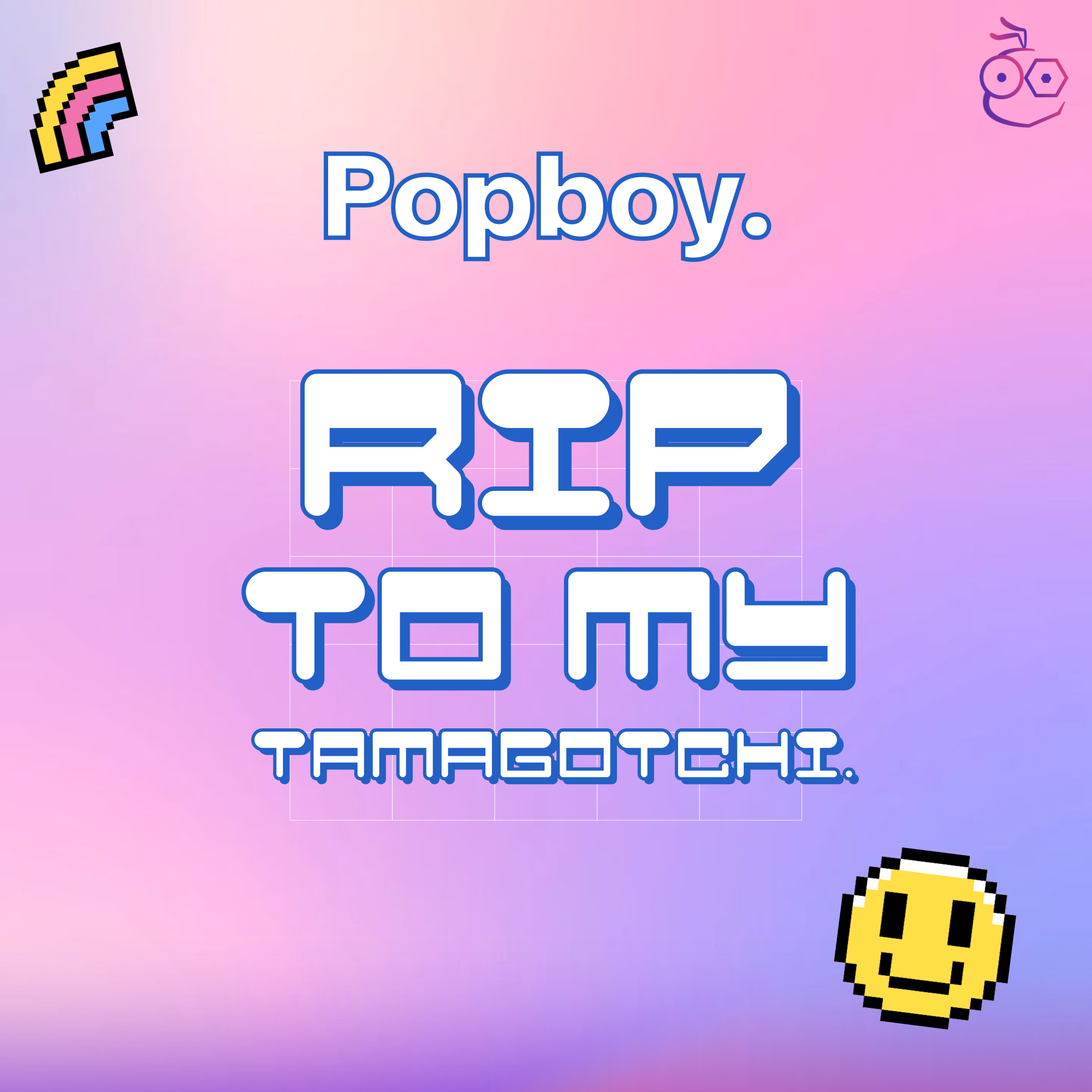
2. Planet Kosmos
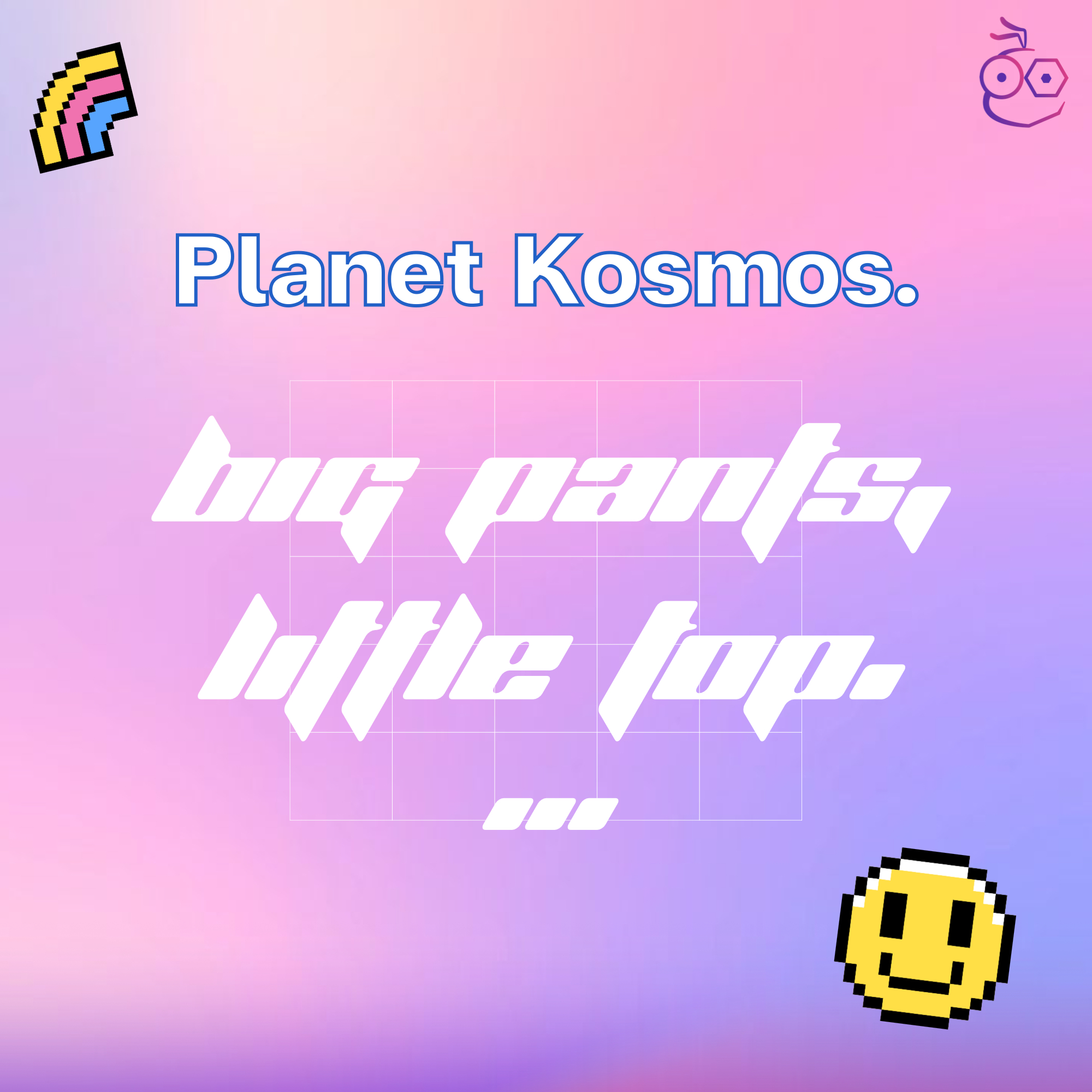
3. Troglodyte Pop
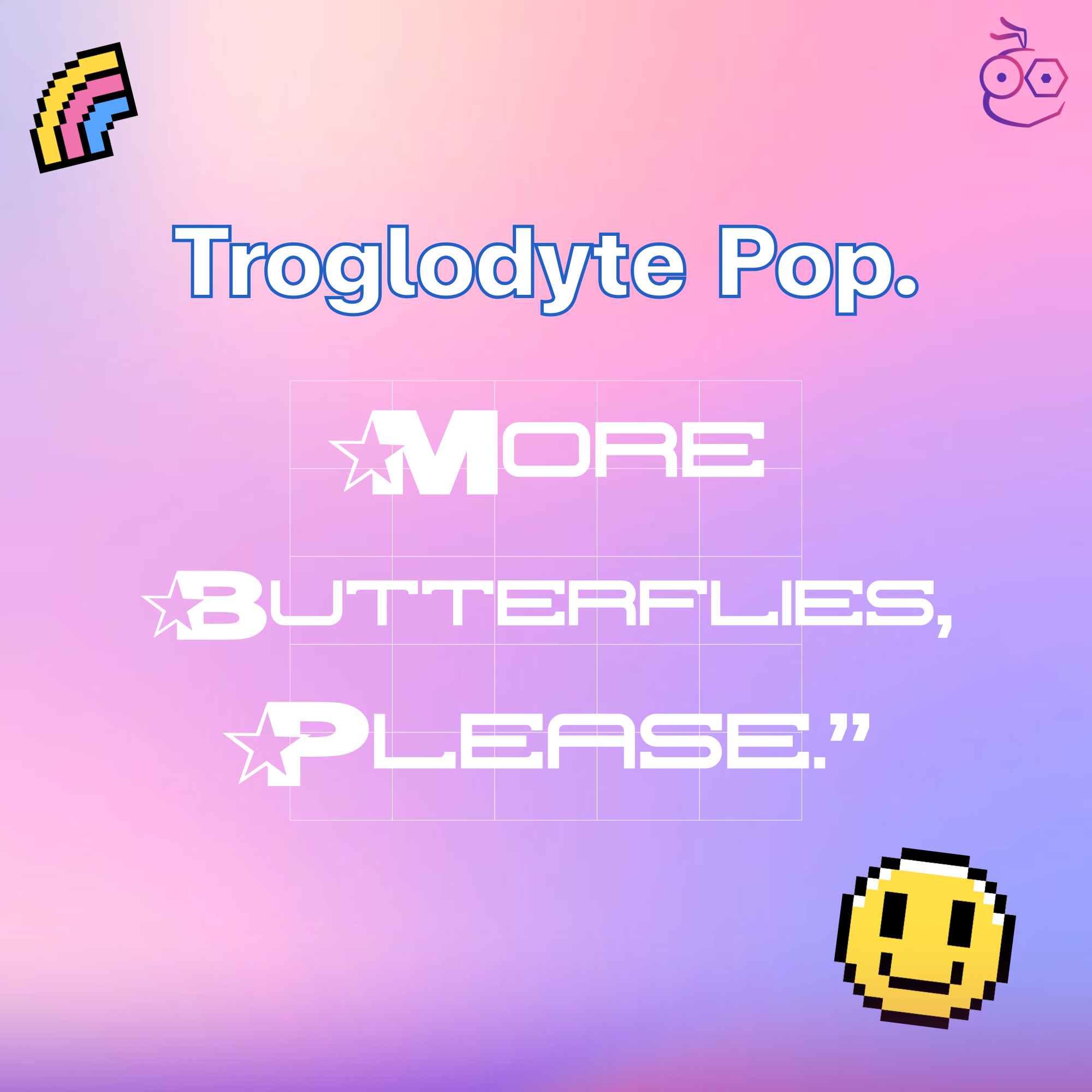
4. Bubblicious
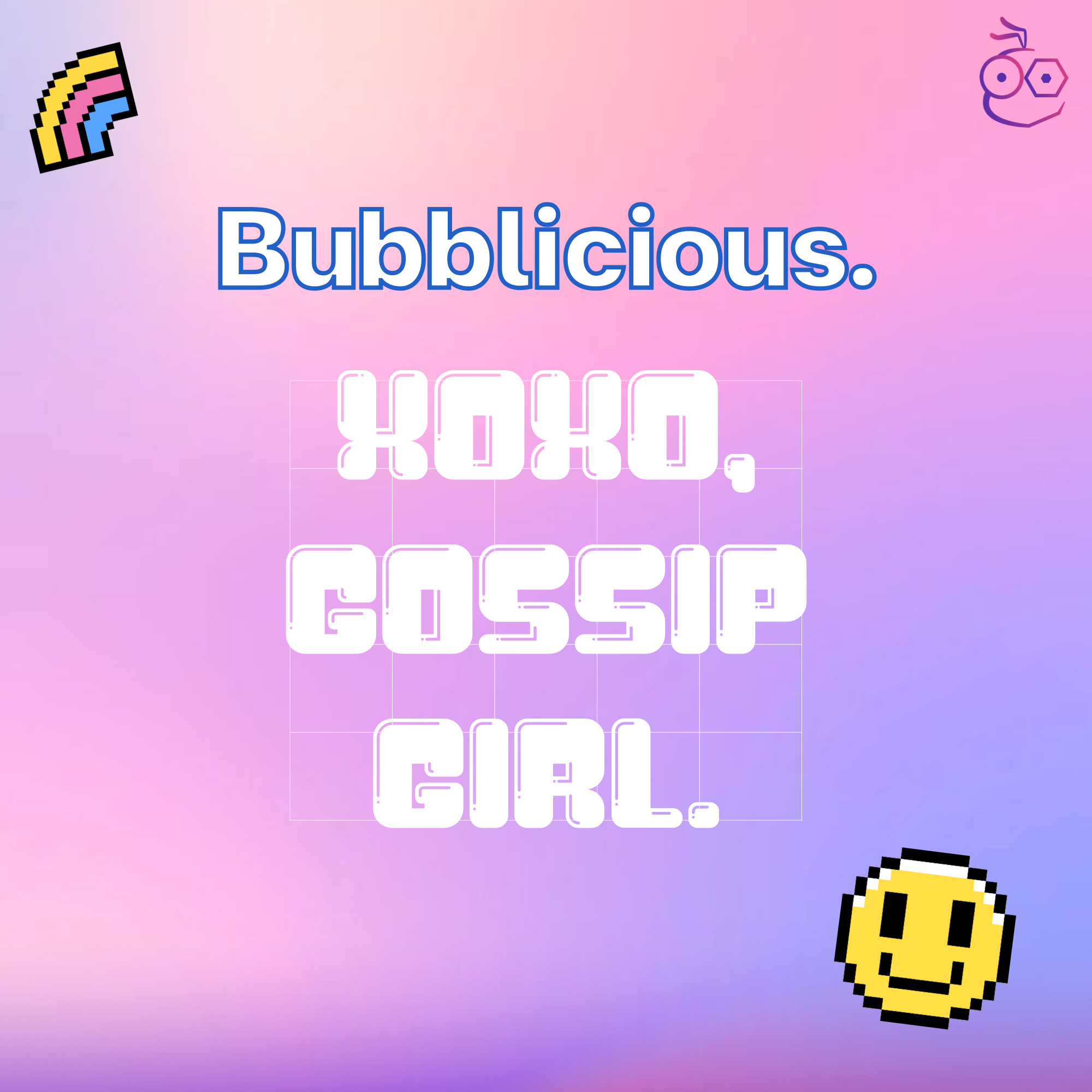
5. GauFontPopMagic
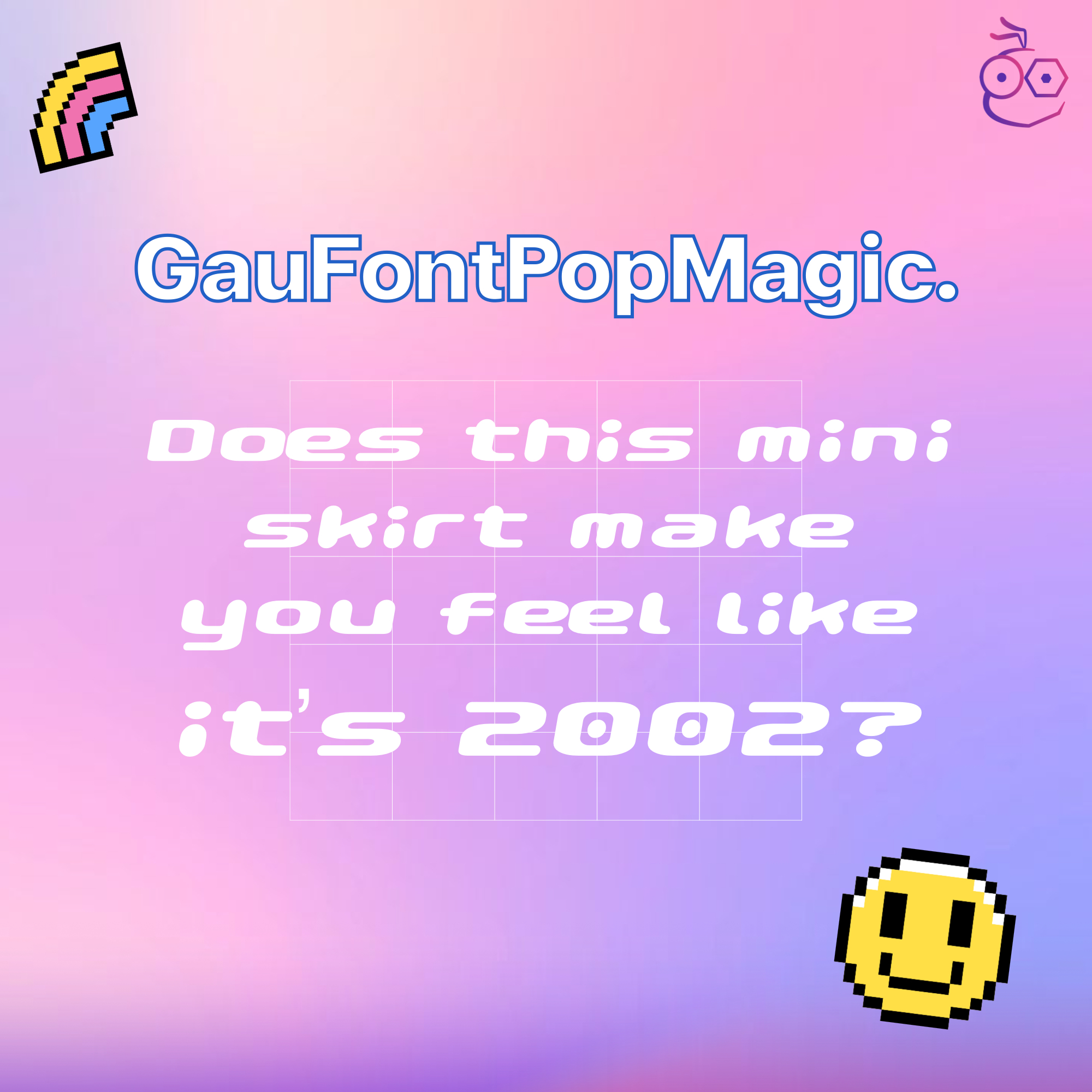
6. a•space
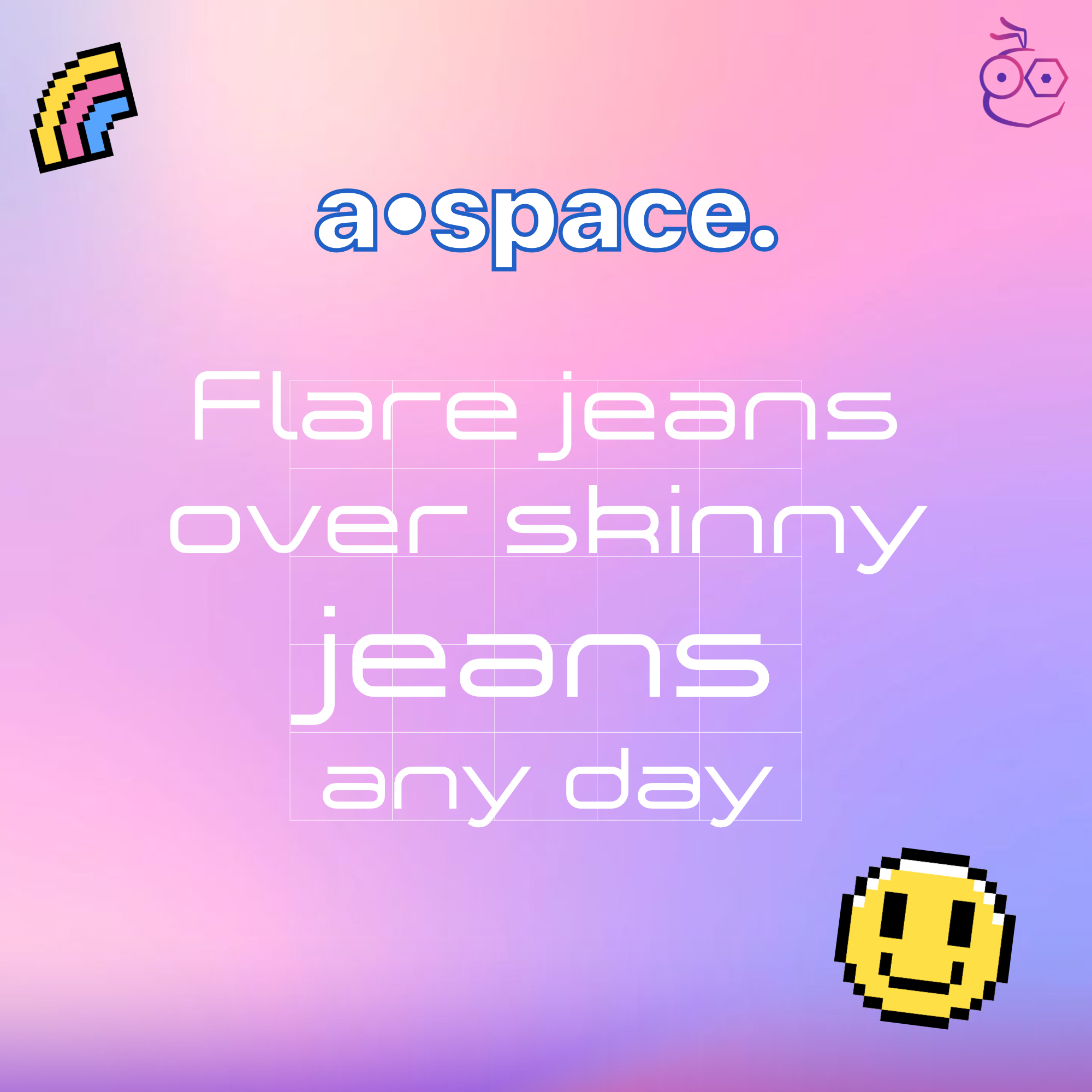
7. Pocket Ball
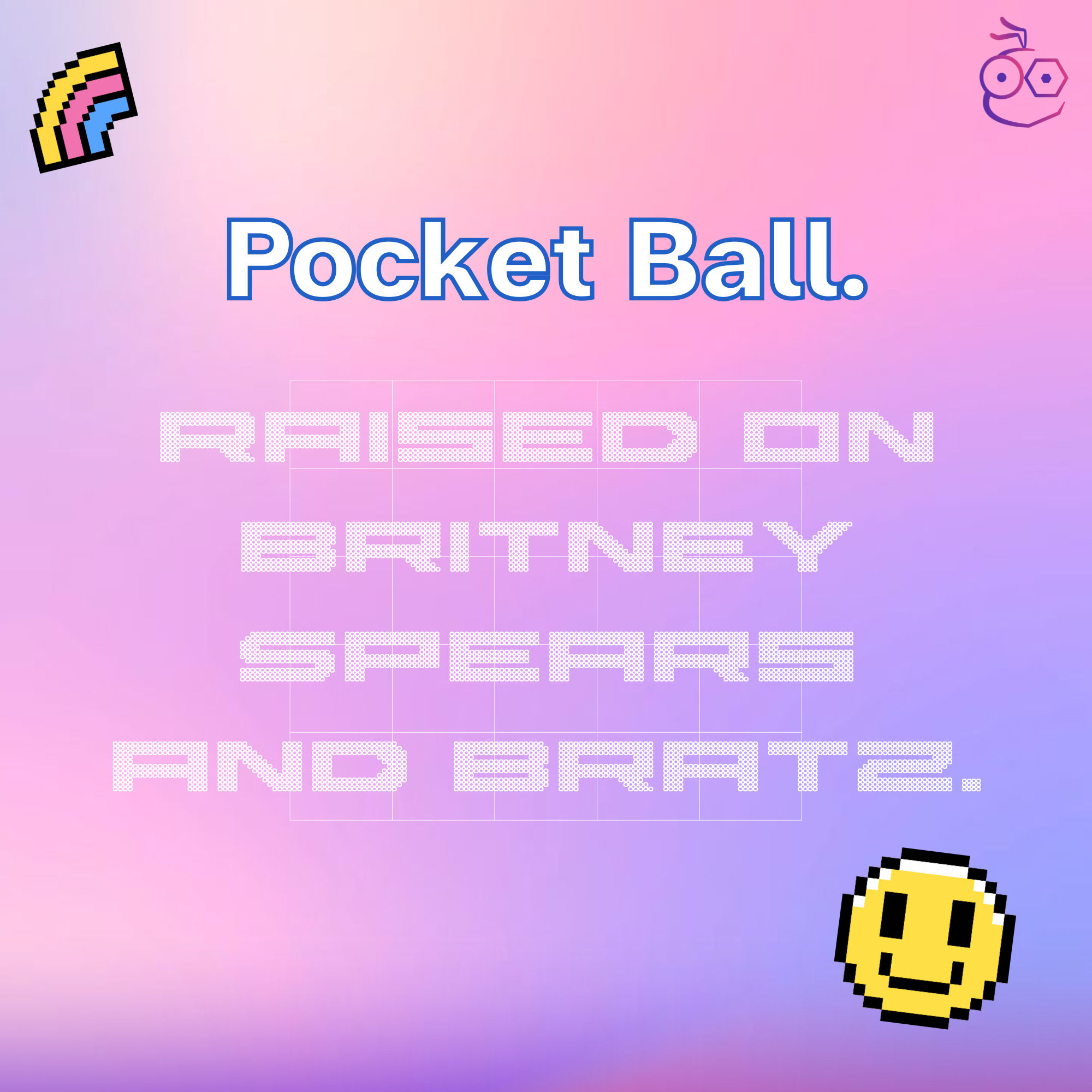
8. Space Age
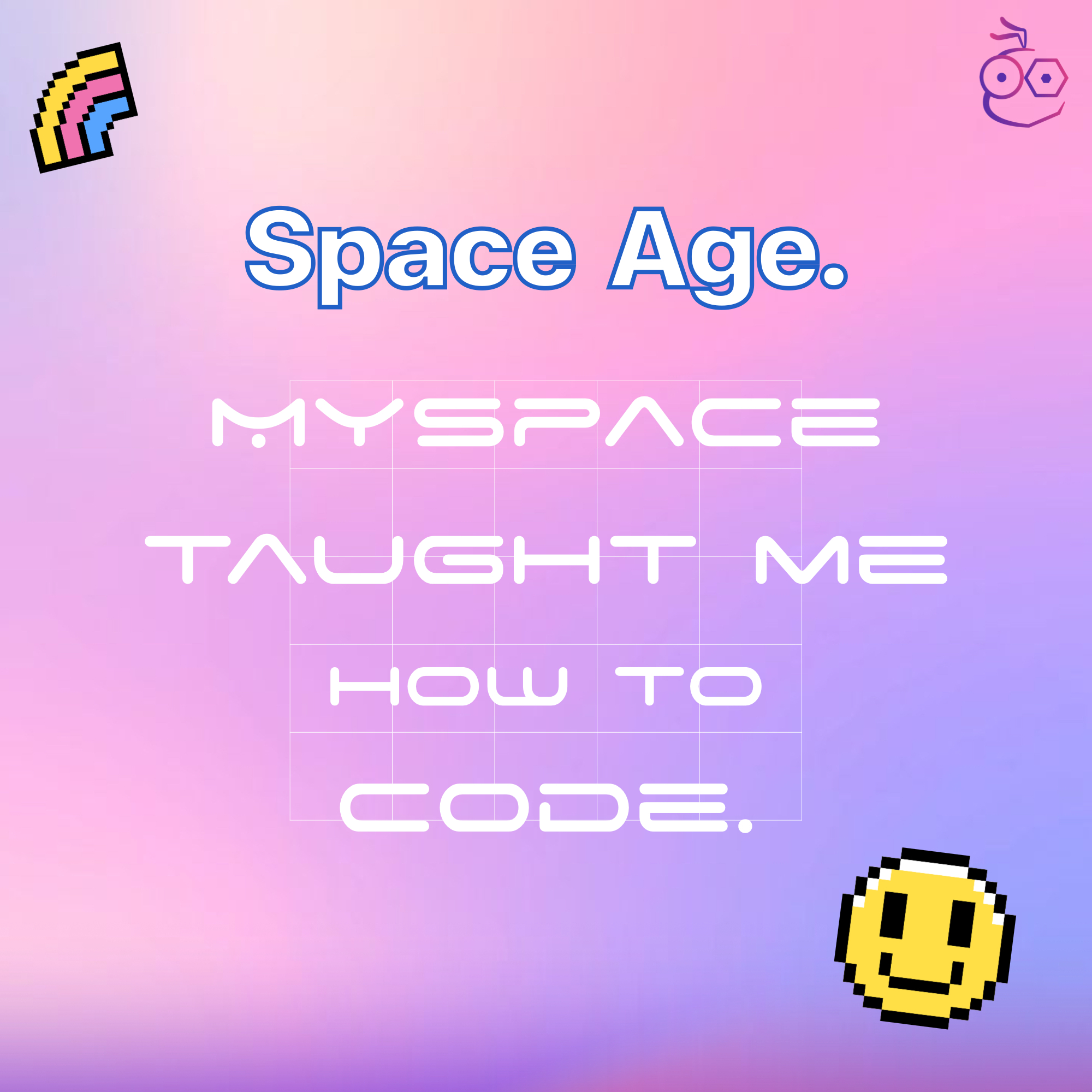
9. Nulshock
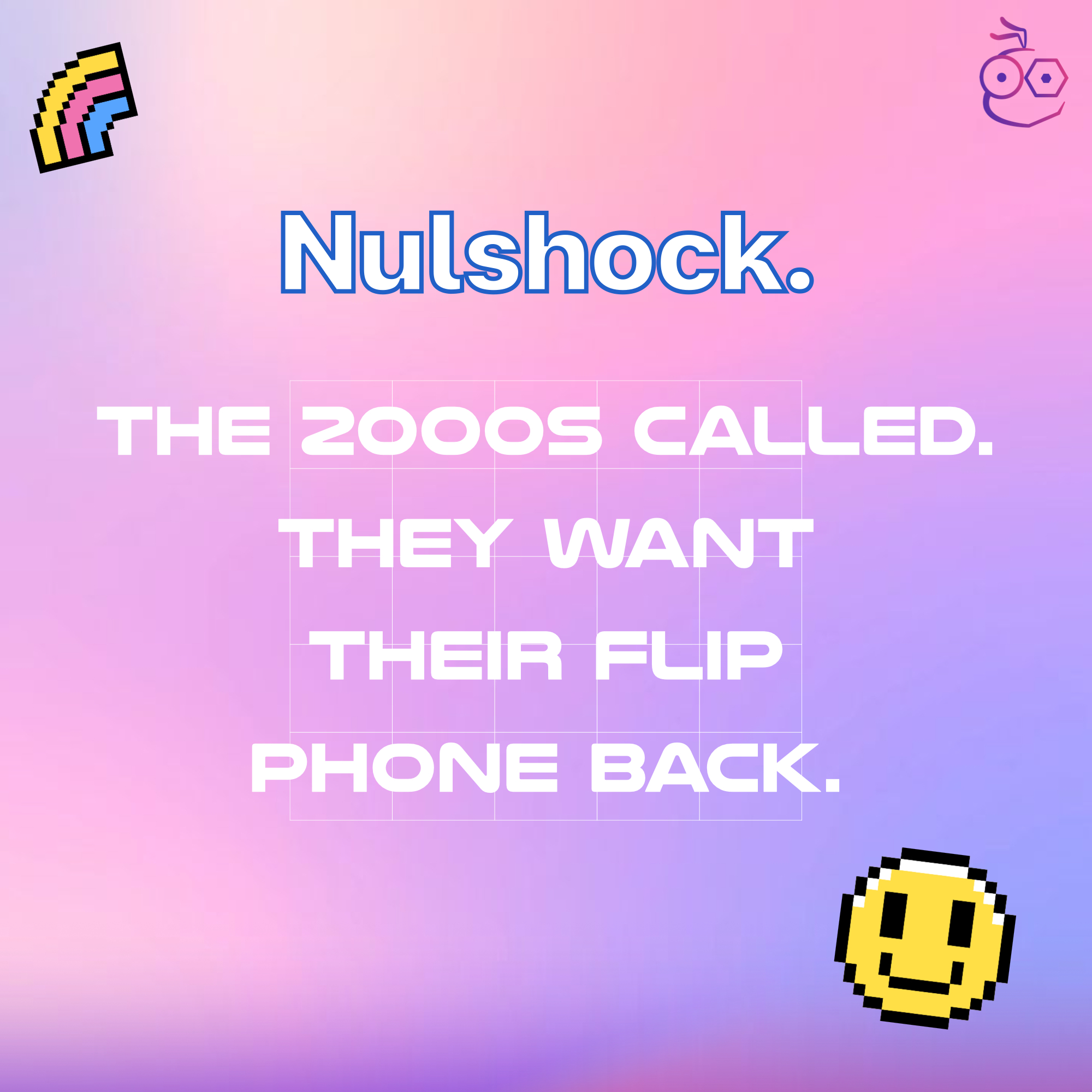
10. Dodopop